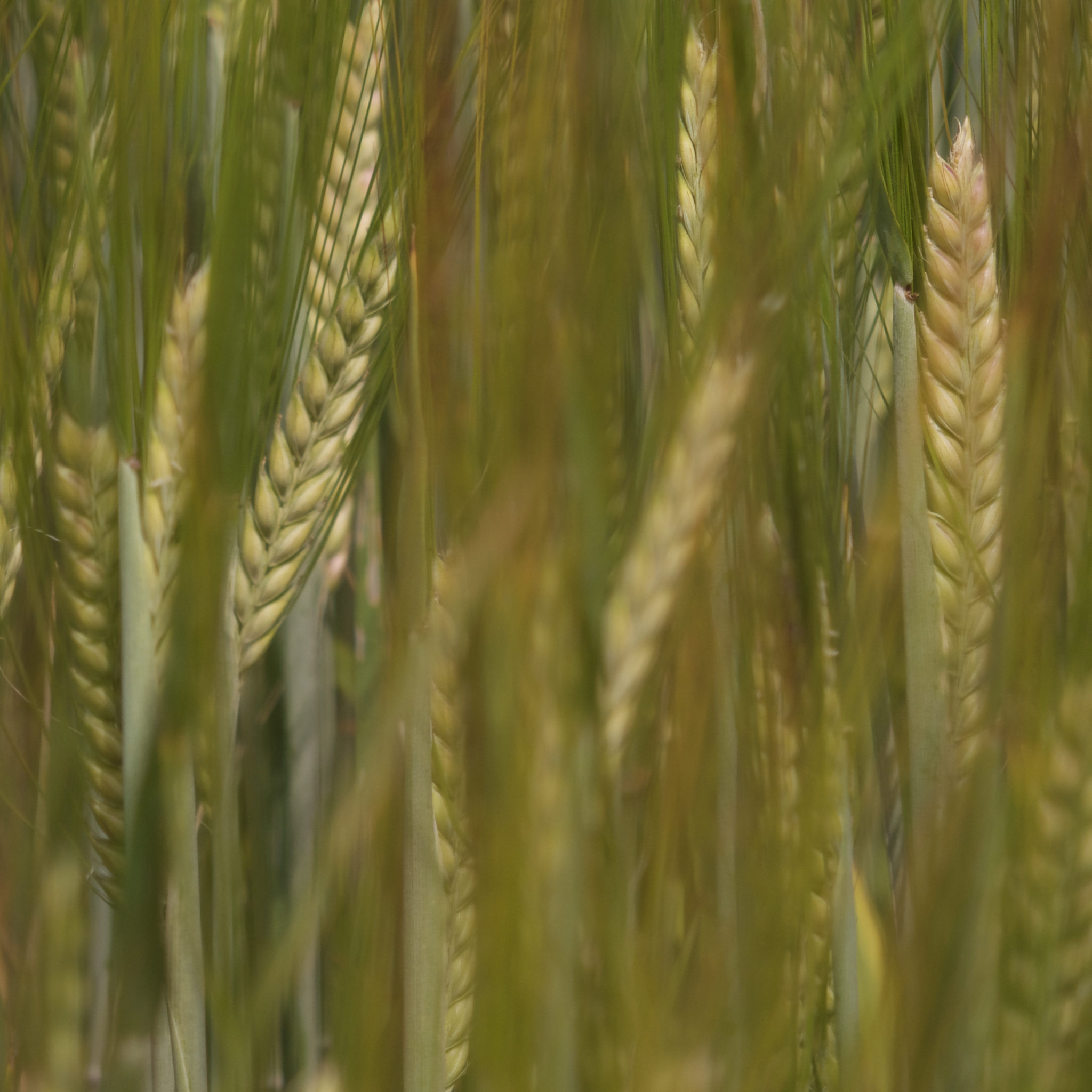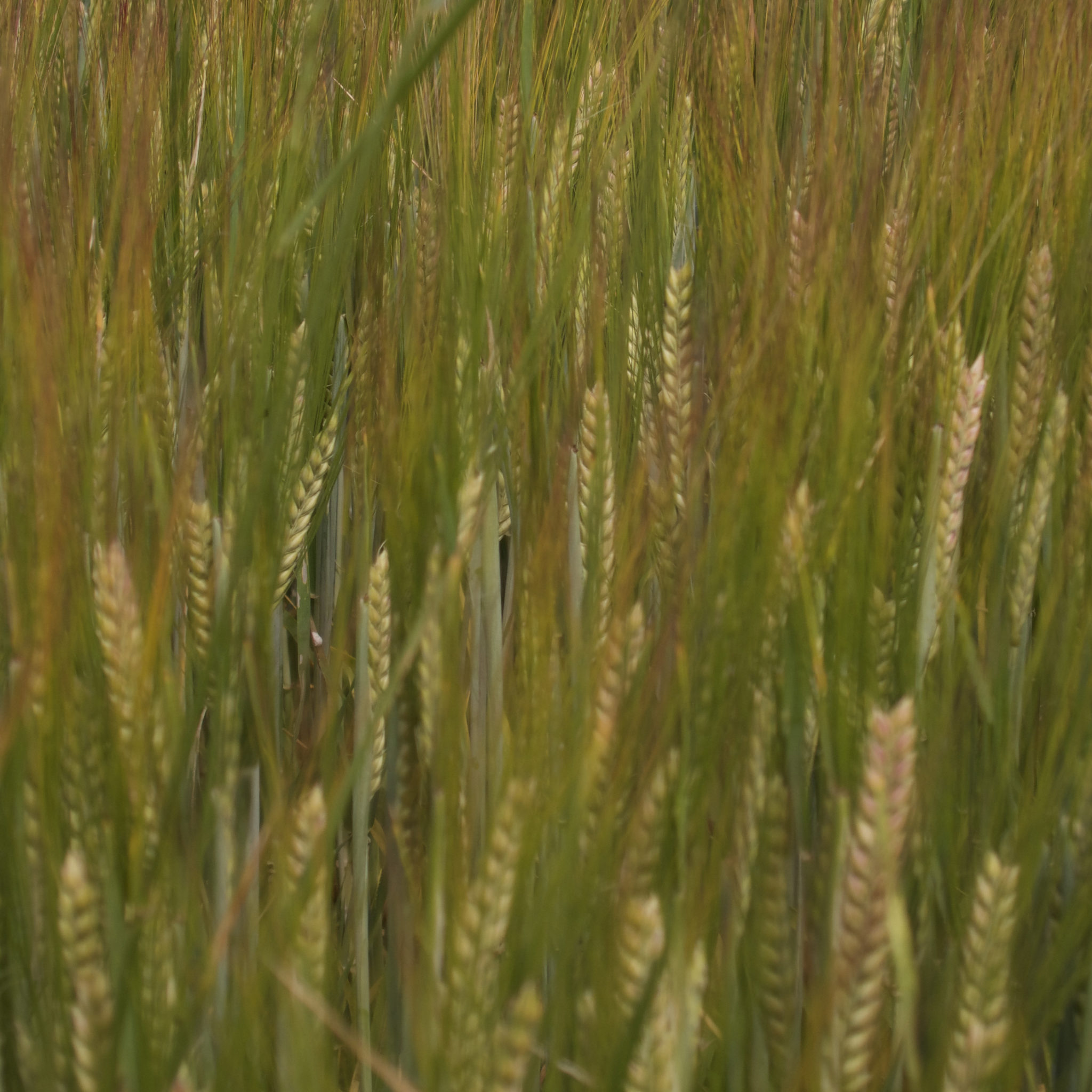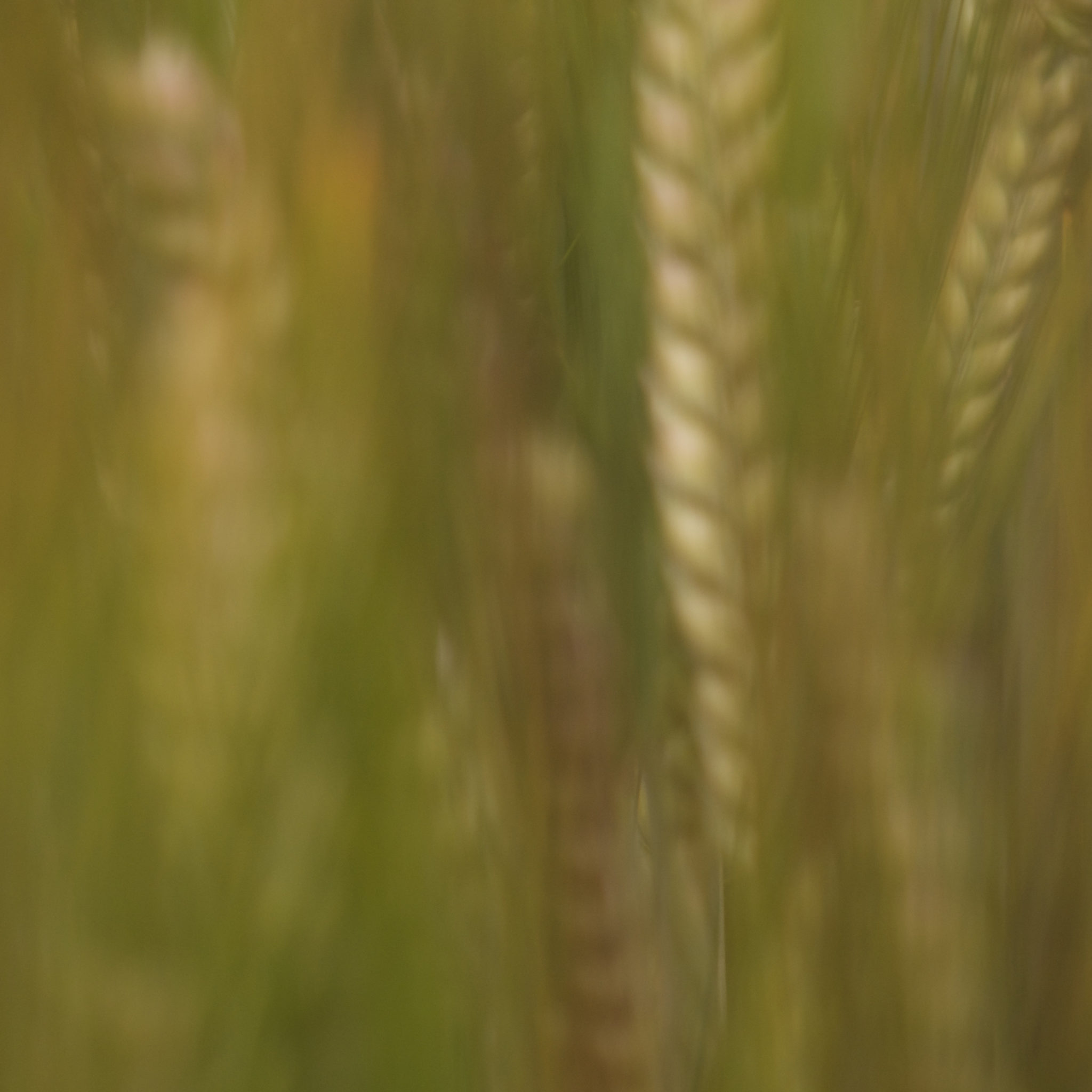
Dans le cadre de cette résidence création sortira un livre, en septembre. Un beau livre photographique, d’art, de linguistique aussi un peu, jouant avec les lettres, mots et images, de sémiologie ludique, à destination des enfants.
Une contemplation livrée en image autour de la formation du langage, des mots. Les lettres se sont promenées, sur le territoire de la résidence, la communauté de communes, et des mots se sont formés. ROUGE, ORGUE, OGRE, ORGE…
Le livre en cours va reprendre cette errance des lettres rouges, et comment elles trouvent entre elles un ordre, pour former mot quand cela est nécessaire pour dire. Selon le lieu, ORGUE dans l’église de Rexpoede, OGRE aux chateaux d’Esquelbecq et West-Cappel, ORGE dans un champ, ROUGE sur un lieu commémorant un massacre anglais…
L’endroit formant idée, sensation, qu’il faut, pour partager, mettre en forme.
Un va et vient entre la chose et le mot.
Ici, en images, un petit bout d’ORGE, dans un champ bientôt moissonné de Quaedypre.